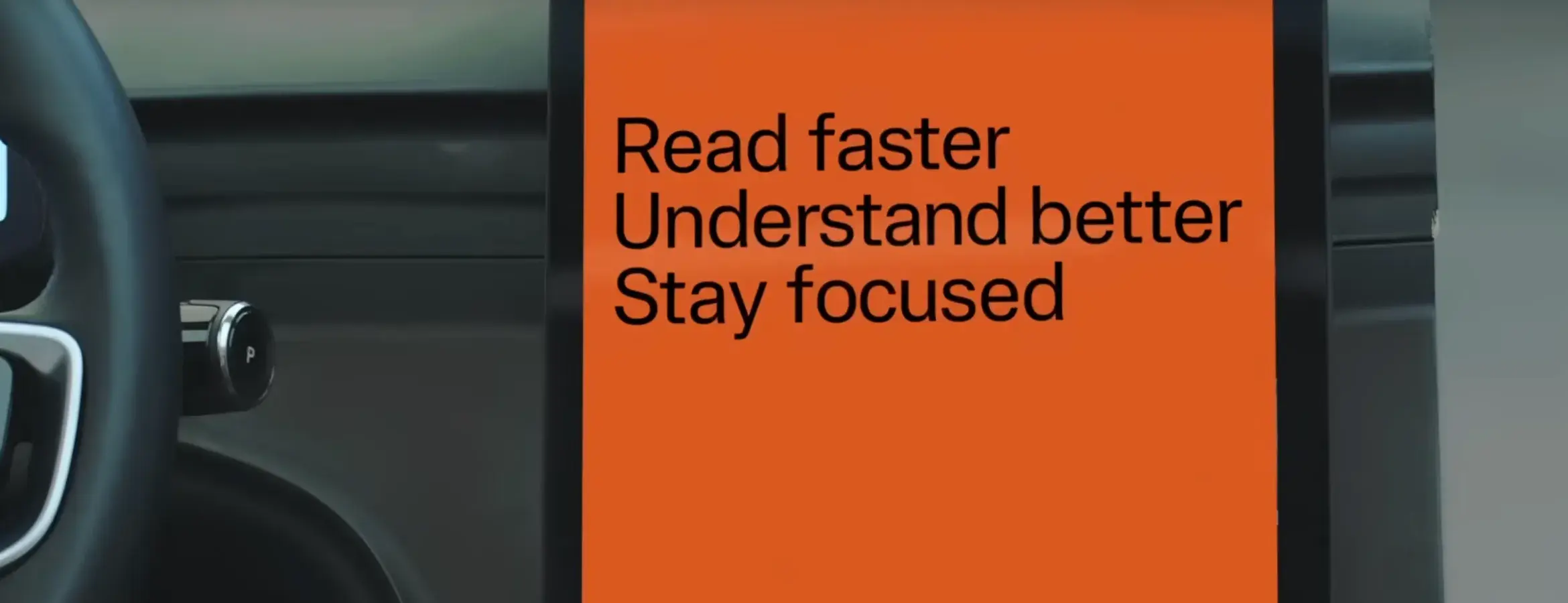
Un levier de sécurité embarquée.
Volvo Cars a dévoilé Volvo Centum, une nouvelle police de caractères développée avec l’agence typographique Dalton Maag pour renforcer la lisibilité des informations dans ses véhicules. Cette création découle d’une démarche où chaque élément – forme, espacement, poids des caractères – a été pensé pour faciliter la lecture en un regard, réduisant l’effort cognitif du conducteur face à des écrans de plus en plus omniprésents dans l’habitacle. Et maximisant son attention sur la route. La typographie ne se contente plus d’être un simple ornement visuel : elle devient un outil fonctionnel au service de la sécurité routière. Sujet au centre de la dernière campagne de la marque avec VML.
L’intérêt de Volvo Centum se joue à plusieurs niveaux : outre une optimisation de la lisibilité en mouvement, la police est conçue pour fonctionner dans des conditions variées – vitesse, luminosité, mobilité – et pour être déployée sur tous les supports numériques, de l’interface du système d’infodivertissement aux panneaux d’affichage externes. Elle prend en charge plus de 800 langues, y compris des écritures complexes comme le chinois, l’arabe ou le japonais, garantissant une cohérence globale de l’expérience utilisateur. Baptisée en référence au centenaire de la marque prévu en 2027, la police fera sa première apparition dans le modèle 100% électrique EX60 (promettant une autonomie record +800km) avant un déploiement plus large via mises à jour OTA (Over-the-air programming).
Cette initiative s’inscrit dans une tendance plus large du design automobile, où les éléments graphiques ne répondent plus uniquement à des logiques esthétiques, mais deviennent des vecteurs d’efficacité et de sécurité. Dans un contexte où les véhicules se métamorphosent en environnements numériques complexes, Volvo Centum illustre comment des détails souvent invisibles peuvent influer sur l’expérience de conduite et, potentiellement, sur la réduction des distractions. En replaçant la typographie au cœur de son interface, Volvo pose les bases d’un dialogue plus clair entre l’humain et la machine, ouvrant la question de l’impact des choix graphiques sur la sécurité future des interfaces embarquées.